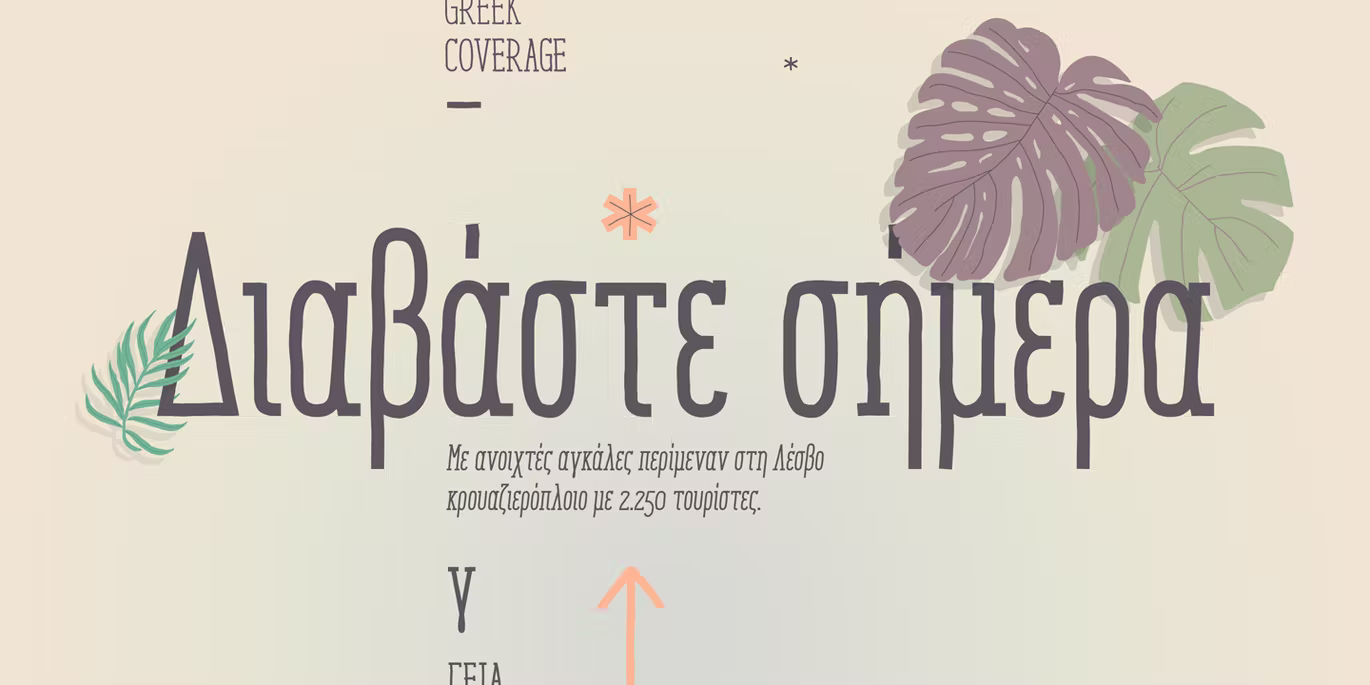
Enyo Slab Font
Description de Enyo Slab Font
Enyo Slab est une police manuscrite décorative, d’affichage et de dalle. Cette police donnera un aspect informel à votre travail ! Il peut être utilisé pour une petite quantité de texte, et spécialement pour l’affichage en raison de sa qualité de glyphe.
Enyo propose des fonctionnalités OpenType, notamment **ligatures, suppléants, petites majuscules, chiffres scientifiques supérieurs/inférieurs, chiffres à l’ancienne, fractions, zéro barré et crénage. **
Cette police manuscrite a une large couverture de glyphes, prend en charge au moins 133 langues, dont l’anglais, l’espagnol, le français, l’allemand, l’italien, le portugais, le suédois, le polonais, le tchèque, le vietnamien et le russe, entre autres. Enyo Slab propose également les alphabets cyrillique et grec.
Vue des polices de la dalle Enyo